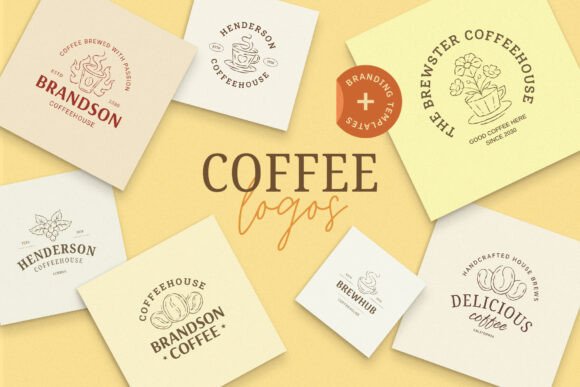
Whimsical Cafe & Bakery Branding Kit
適切なデザイン要素を見つけるのは難しい場合がありますが、Whimsical Cafe & Bakery Branding Kitは作品を即座に引き立てる優れたコレクションを提供します。
精密に作られたWhimsical Cafe & Bakery Branding Kitは、クリーンなベクター、滑らかなタイポグラフィ、そして安心のための商用ライセンスを提供します。